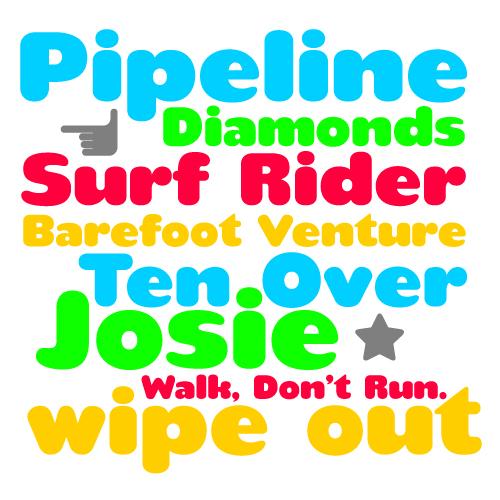
Der Trend zu runden Lettern in extremis:
Teaspoon von Haley Fiege bei Canada Type.
Teaspoon was originally designed by Haley Fiege as a project-specific font in 2007, then completed and produced by Canada Type for commercial viability in 2008. With a personality that can only be described as "ironic cute", it serves as a much needed alternative for the old overused poster faces, such as Cooper Black and Gill Sans Extra Bold. Words that look good set in Teaspoon include puppies, rainbows, salmonella poisoning and Tom Cruise.